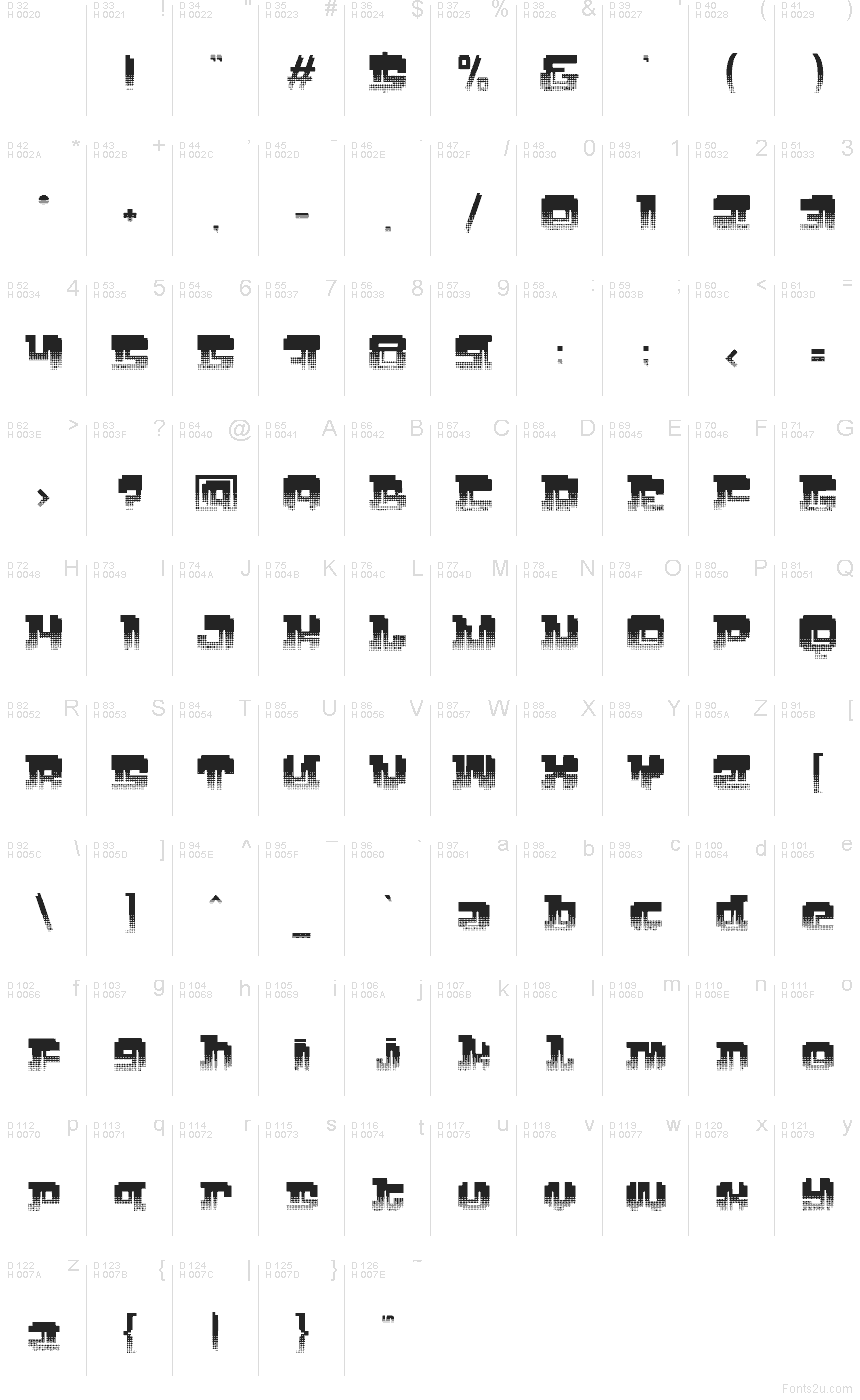
Techno Wave Six od Putracetol Studio je futuristické bezplatné písmo typu display, které definuje ostrá obdélníková horní hrana přecházející do svislých tečkovaných cest. Tato opakující se textura pixelů a rastru dodává písmu digitální „glitch“ charakter, díky čemuž působí spíše jako součást moderní digitální grafiky než jako generický sci-fi styl.
Font má dostatečnou výraznost pro názvy her, letáky elektronické hudby, náhledy videí na YouTube, úvodní obrazovky aplikací i e-sportové overlaye. Jelikož plná velká písmena přecházejí do vzoru padajících teček, skvěle se hodí pro titulky plakátů nebo grafiku rozhraní, která vyžaduje efekt datového toku, skenovacích linek nebo výpadku signálu bez nutnosti složitého vlastního literního zpracování.